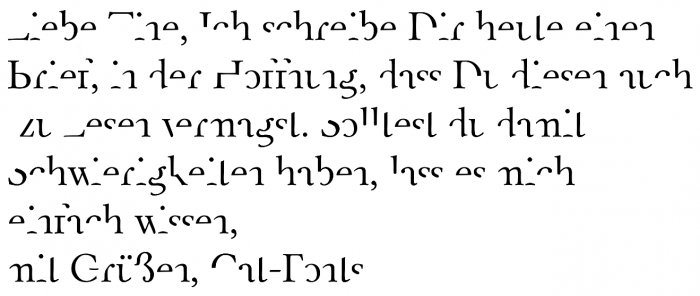
„FF You Can Read Me“-Alternativen
Da könnte man ja z.B. ne Libertine verstümmlen, und sie "Liebe Tine" nennen :-)
„Liebe Tine“ würde ich die Schrift an Deiner Stelle nicht nennen. Rechtlich ist dies zwar sicher kein Problem, aber man könnte dann denken die Schrift käme von LiebeFonts.
War ja auch nur als Verballhornung von Libertine gedacht, mehr ein Scherz als wirkliche Planung. "Readers Frightning" könnte ich mir eher vorstellen.
Aber auf de Liebe Tine von LiebeFonts wär ich schon neugierig :-)
Was war damals eigentlich eher, das MDR-Logo oder die Schrift?
Ich glaube der Font war eher und das Logo wurde dann für den mdr von dem Font abgeleitet. Das alte Logo vom mdr war schwarz-rot-gold, würde mich mal interessieren wer das damals gestaltet hat. Der Font ist bestandteil von Fuse 1, die habe ich im Original-Pappschuber auf Diskette noch hier und doppelt, falls die jemand günstig erwerben will kann mir gerne schreiben.
Kann mich halt noch dunkel an einen Fernsehbeitrag erinnern, wo der Logodesigner inkl. Gestaltungsprozess dazu vorgestellt wurde. In meiner Erinnerung hat man die Buchstaben da unter anderem in skizzierter Form gezeigt, daher die Frage.
Edit – Wikipedia sagt aber auch:
Das MDR-Logo generell ist aus einer Schrift von Phil Baines (Fuse) gesetzt, die »FF You can read me« heißt.